Use Any Font 플러그인을 이용해 워드프레스 나눔바른고딕을 적용하려는 분들이 많습니다. 기본 글꼴이 사이트 분위기와 어울리지 않거나, 한글 글자가 어색하게 보이는 경우가 있기 때문입니다. 특히 한글 위주로 글을 작성하는 블로그는 폰트에 따라 화면 느낌이 꽤 달라지는 편입니다.
글자 간격이 답답해 보이거나 오래된 기본 폰트 느낌이 강하면 본문 전체가 무겁게 보일 수 있습니다. 그래서 웹폰트를 불러오는 대신 직접 폰트 파일을 업로드해서 적용하는 방법을 사용하는 경우도 많습니다. 외부 폰트 요청을 줄일 수 있다는 점 때문에 이런 방식을 선택하는 사람들도 있습니다.
워드프레스에서 폰트를 바꾸는 작업은 단순히 글꼴만 바꾸는 일이 아닙니다. 화면 전체 가독성, 로딩 속도, 브라우저 표시 방식에 영향을 줄 수 있습니다. 특히 한글 폰트는 파일 용량이 큰 편이라 무분별하게 여러 개를 넣으면 페이지가 늦게 열릴 수 있습니다.
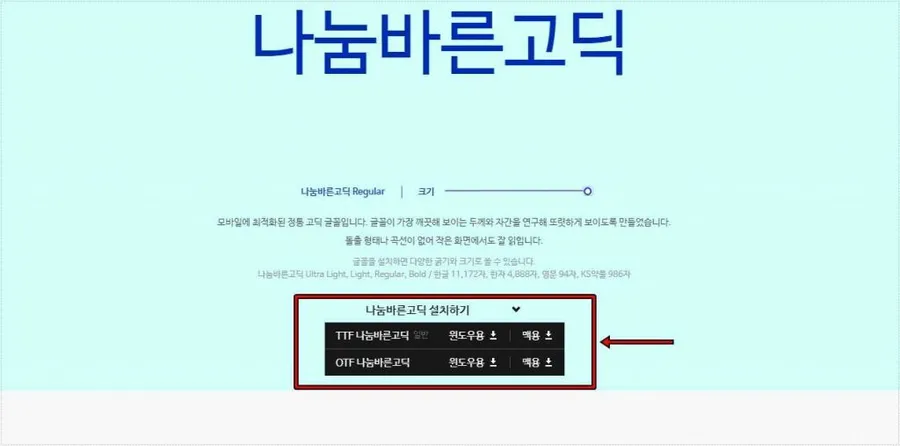
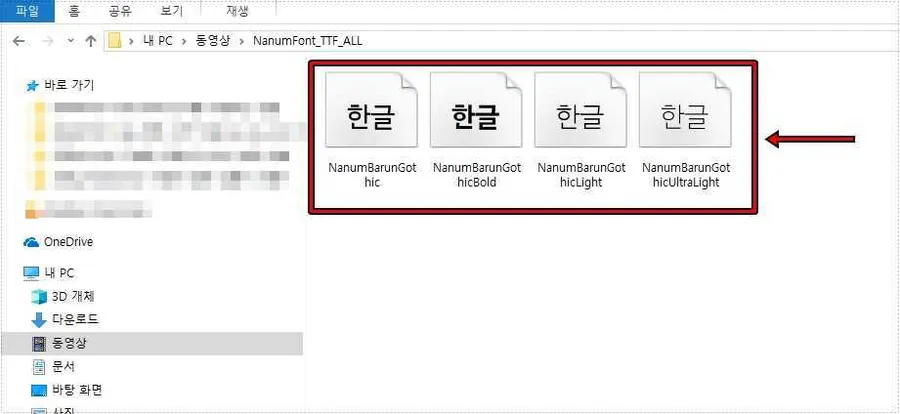
예를 들어 본문만 바꾸고 싶다면 Paragraphs 항목을 선택하고, 제목까지 바꾸고 싶다면 Heading 항목을 함께 선택합니다. 모든 요소에 한 번에 적용하면 사이트 분위기가 갑자기 달라질 수 있습니다. 그래서 처음에는 본문이나 제목처럼 한 영역만 적용한 뒤 화면을 확인하는 편이 안전합니다.
Custom Elements 영역에는 직접 CSS 선택자를 입력할 수도 있습니다. 특정 영역에만 워드프레스 나눔바른고딕을 넣고 싶을 때 이 방식이 필요합니다.
적용 후 확인해야 할 부분
워드프레스 나눔바른고딕 적용이 끝났다면 사이트 화면을 바로 확인해야 합니다. 관리자 화면에서 저장만 했다고 끝나는 것이 아닙니다. 확인할 부분은 아래와 같습니다.
- 본문 글자가 정상 표시되는지
- 제목 굵기가 너무 무겁지 않은지
- 모바일 화면에서 줄 간격이 자연스러운지
- 메뉴 글자가 깨지지 않는지
- 페이지 로딩이 느려지지 않았는지
- 기존 테마 폰트와 충돌이 없는지
특히 한글 폰트는 파일 용량이 커질 수 있기 때문에 적용 후 속도 변화도 확인하는 편이 좋습니다. 너무 많은 폰트를 올리면 화면이 늦게 그려지는 느낌이 생길 수 있습니다.
폰트 적용 후 기대할 수 있는 변화
나눔바른고딕을 적용하면 한글 글자의 모양이 더 일정하게 정리됩니다. 특히 본문이 많은 블로그에서는 글자 모양이 안정되면서 읽는 흐름이 부드러워지는 경우가 많습니다. 다만 폰트 변경은 디자인 요소이면서 동시에 로딩 요소이기도 합니다. 그래서 예쁜 글꼴을 넣는 것보다 필요한 위치에만 적용하는 것이 중요합니다.
워드프레스 나눔바른고딕 적용은 사이트 분위기를 바꾸는 작업이지만, 잘못 설정하면 속도 문제나 표시 오류로 이어질 수 있습니다. 그래서 플러그인 설치, API 키 설정, 폰트 업로드, 적용 위치 선택 순서로 차근차근 진행하는 편이 안전합니다.
마무리
Use Any Font 플러그인을 사용하면 워드프레스 나눔바른고딕을 직접 업로드해서 적용할 수 있습니다. 핵심은 폰트를 많이 넣는 것이 아니라 필요한 파일만 올리고, 적용 범위를 정확히 정하는 것입니다.
본문이나 제목부터 천천히 적용해 보면 사이트 분위기와 가독성을 함께 조정할 수 있습니다.